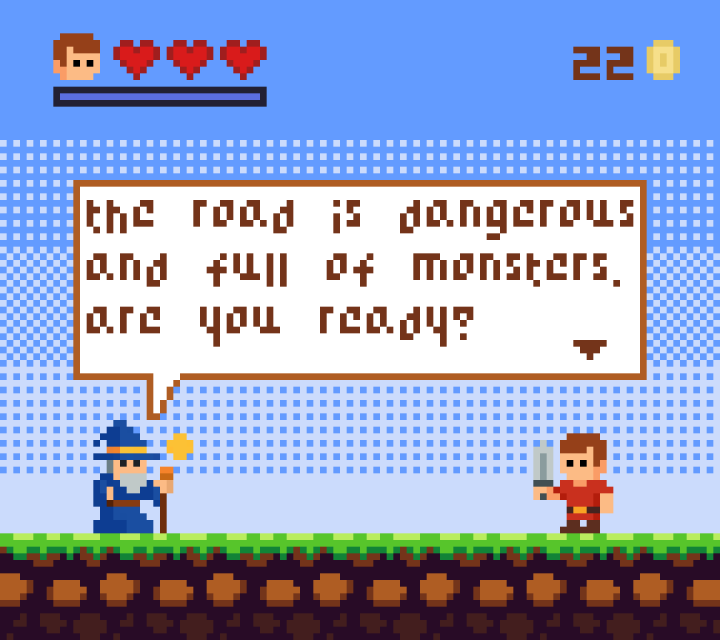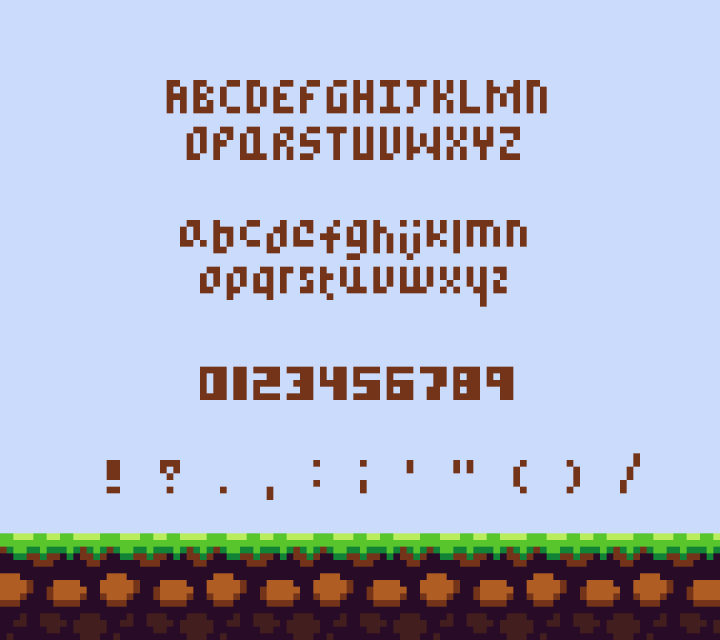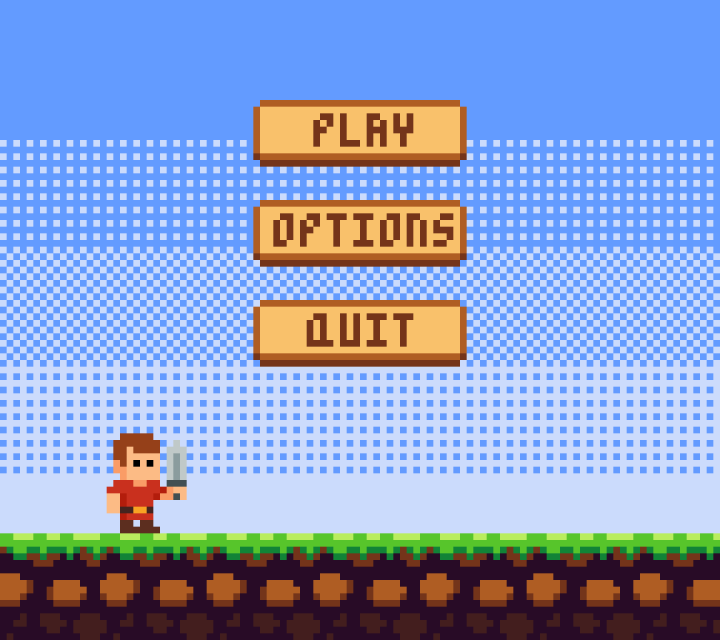
免费的经典基础像素RPG游戏字体素材,用这款免费像素RPG字体,让你的复古冒险栩栩如生!这款字体专为RPG游戏、像素艺术项目和独立游戏开发而设计,呈现经典的8位和16位风格,非常适合用于对话框、菜单、用户界面、HUD、物品名称和标题。
无论您是在制作奇幻角色扮演游戏、地牢探索游戏、roguelike游戏、冒险游戏还是复古风格的项目,这款字体都易于阅读,同时保留了经典像素游戏的怀旧外观。
- 复古像素风格,灵感源自经典角色扮演游戏
- 小尺寸下清晰易读
- 非常适合用于游戏用户界面和对话
- 包括大写字母
- 包括小写字母
- 包括数字
- 包含常用符号和标点符号